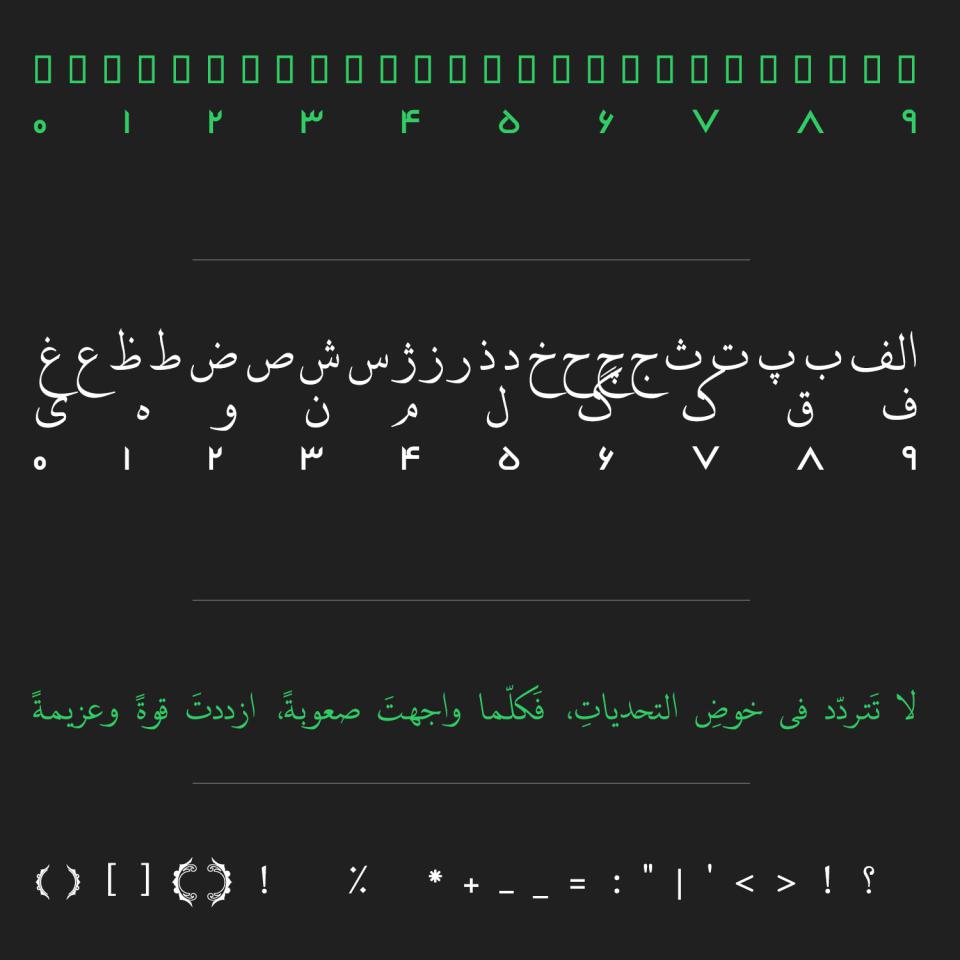
فونت نبی فارسی
فونت نبی، یک انتخاب ایده آل برای کسانی است که به دنبال ظرافت و خوانایی در متون فارسی خود هستند. این فونت با طراحی منحصر به فرد خود، تجربه ای متفاوت از خواندن و نوشتن را ارائه می دهد. اگر به دنبال فونتی هستید که هم در متون چاپی و هم در صفحات وب، جلوه ای زیبا و حرفه ای به نوشته های شما ببخشد، فونت نبی گزینه ای عالی است.
یکی از ویژگی های برجسته این فونت، طراحی دقیق حروف و اعراب آن است که باعث می شود متن شما به راحتی خوانده شود و در عین حال زیبایی خاصی داشته باشد. این فونت به خصوص برای متون طولانی و کتاب ها بسیار مناسب است، زیرا خستگی چشم را کاهش می دهد و خواندن را لذت بخش تر می کند. همچنین، فونت نبی در طراحی های گرافیکی و وب سایت ها نیز کاربرد فراوانی دارد و می تواند به بهبود ظاهر و جذابیت بصری آنها کمک کند.
فونت نبی، با پشتیبانی کامل از حروف فارسی و اعراب، اطمینان می دهد که متن شما بدون هیچ مشکلی نمایش داده شود. این فونت به صورت رایگان در دسترس است و شما می توانید به راحتی آن را دانلود و در پروژه های خود استفاده کنید. اگر به دنبال فونتی هستید که هم زیبا باشد، هم خوانا و هم رایگان، فونت نبی بهترین انتخاب برای شماست. این فونت با طراحی چشم نواز خود، می تواند به نوشته های شما روحی تازه ببخشد و آنها را جذاب تر و حرفه ای تر نشان دهد.